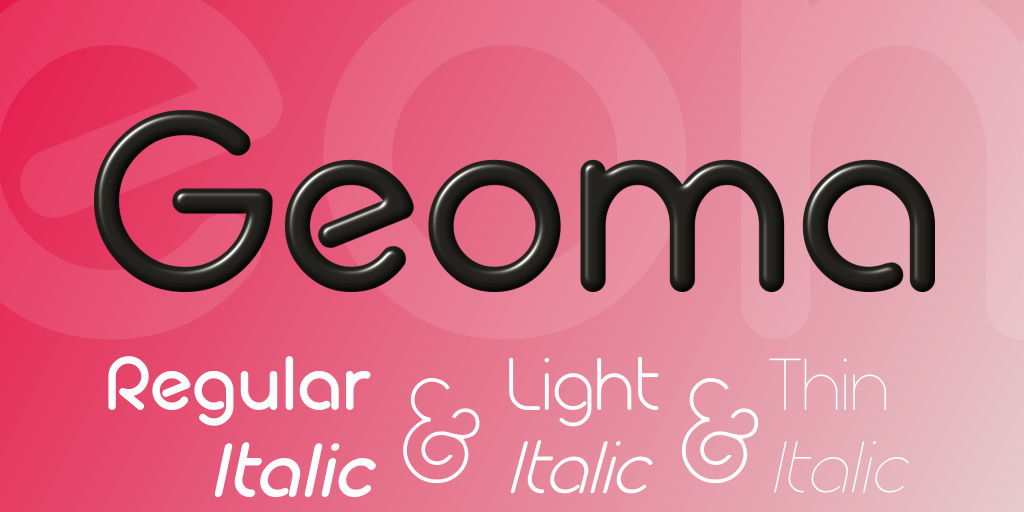
A Geoma Font Family é uma família de fontes display cuidadosamente concebida para oferecer uma experiência visual vibrante e única. Ideal para textos chamativos que se destacam no meio de qualquer projeto, esta família de seis letras foi criada pelo designer Hamilton. As letras da Geoma são caracterizadas por sua curvatura exuberante e suas linhas ativas, que proporcionam um toque de movimento ao seu design. A Geoma é perfeita para uso em logotipos ou títulos destacados, como capas de livros, embalagens de moda, cartazes urbanos ou até mesmo aplicativos móveis. Seu estilo deslizante e dinâmico contrasta agradavelmente com outros tipos mais tradicionais, criando um ar contemporâneo e moderno em qualquer projeto visual. Essa família é perfeita para designers que buscam transmitir uma mensagem forte e vibrante de forma elegante. Se você está interessado em testar uma versão limitada da Geoma Font Family para projetos comerciais, Hamilton oferece um espaço no seu site onde você pode fazer sua solicitação. Seja você um designer profissional ou um iniciante, a Geoma é uma fonte que certamente vale o seu tempo e investimento.